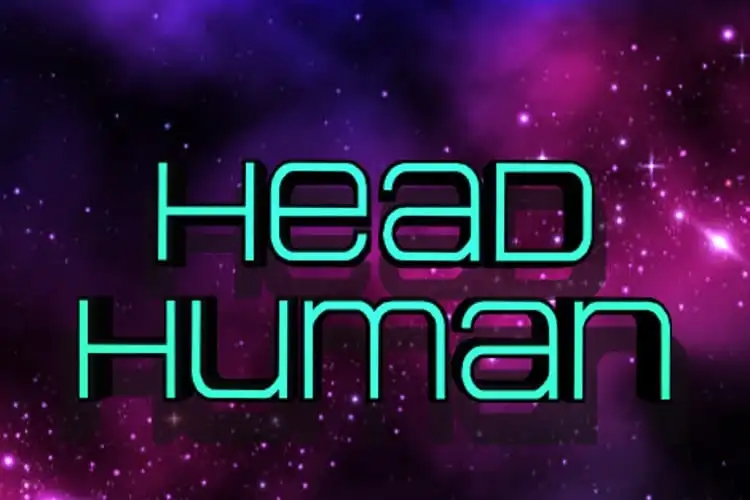
Head Human Display Font é uma seleção rica e variada de 30 versões desenhadas especialmente para quem busca um estilo chamativo e expressivo na sua próxima criação visual. Esta fonte dispõe de variedade, desde a elegância da Regular e Italic até os modos mais fortes como Bold e Heavy, que adicionam uma intensidade poderosa às suas mensagens. Para atender aos diferentes estilos e contextos, Head Human oferece versões esquadrinhadas (Leftalic), semicílias (Sem-Leftalic), alongadas (Condensed) e ampliadas (Expanded). Os tipos 3D e gradacionais permitem uma aparição realista e sofisticada, enquanto os traços nítidos do Outline Italic proporcionam um toque moderno. Entre as várias opções de estilos fortes, incluem-se Bold Sem-Italic que adiciona um toque delicado ao forte impacto da bold, enquanto as versões Condensed e Expanded permitem ajustes perfeitos para diferentes formatos. Finalmente, para atender a uma variedade maior de estilos, o Head Human oferece Academy, um estilo mais elegante e acadêmico, e Title e seu Italic para aplicação em cabeçalhos. Essa riqueza no design é ideal para designers que buscam tanto impacto quanto personalidade, adaptando as suas criações ao espaço específico de cada projeto. Head Human Display Font, uma fonte diversificada projetada especificamente para quem deseja expressar o seu conteúdo de forma única e inovadora.